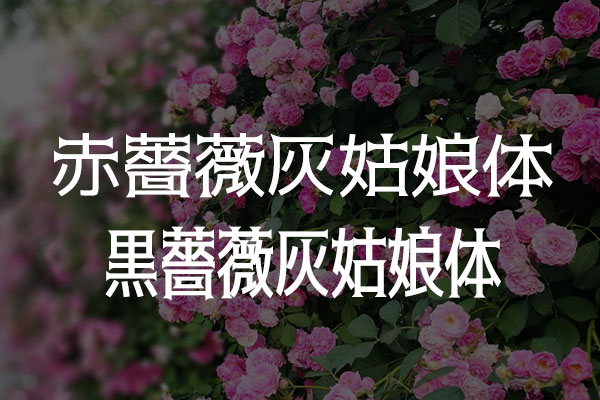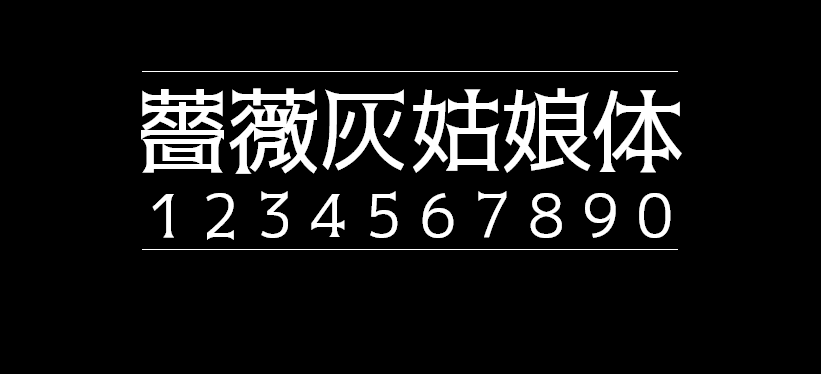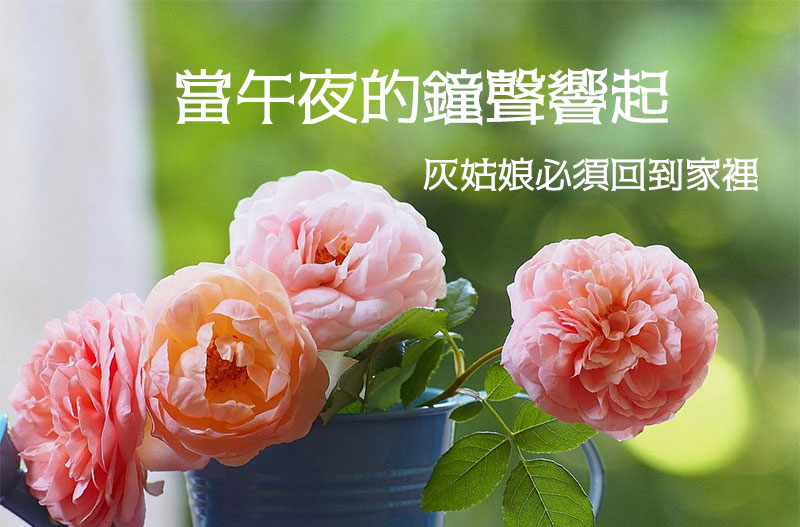
薔薇灰姑娘体
薔薇灰姑娘体是一款充满魔幻神秘色彩的字体,这款字体分为两个版本。分别是 黒薔薇(日文名: 黒薔薇シンデレラ 英文名:kurobara-cinderella)和赤蔷薇(日文名: 赤薔薇シンデレラ 英文名:akabara-cinderella )两款。这两款的区别是, 黒薔薇的字体比较纤细,而赤薔薇的字体比较宽。虽然是日文字体,但是也支持大部分繁体字,简体字支持的就比较少了。 薔薇灰姑娘体是基于开源字体M+ FONTS改造制作的字体,所以也遵循M+ FONTS的开源授权规则,可以自由地使用该字体,可以用于任何场合,包括免费商用。